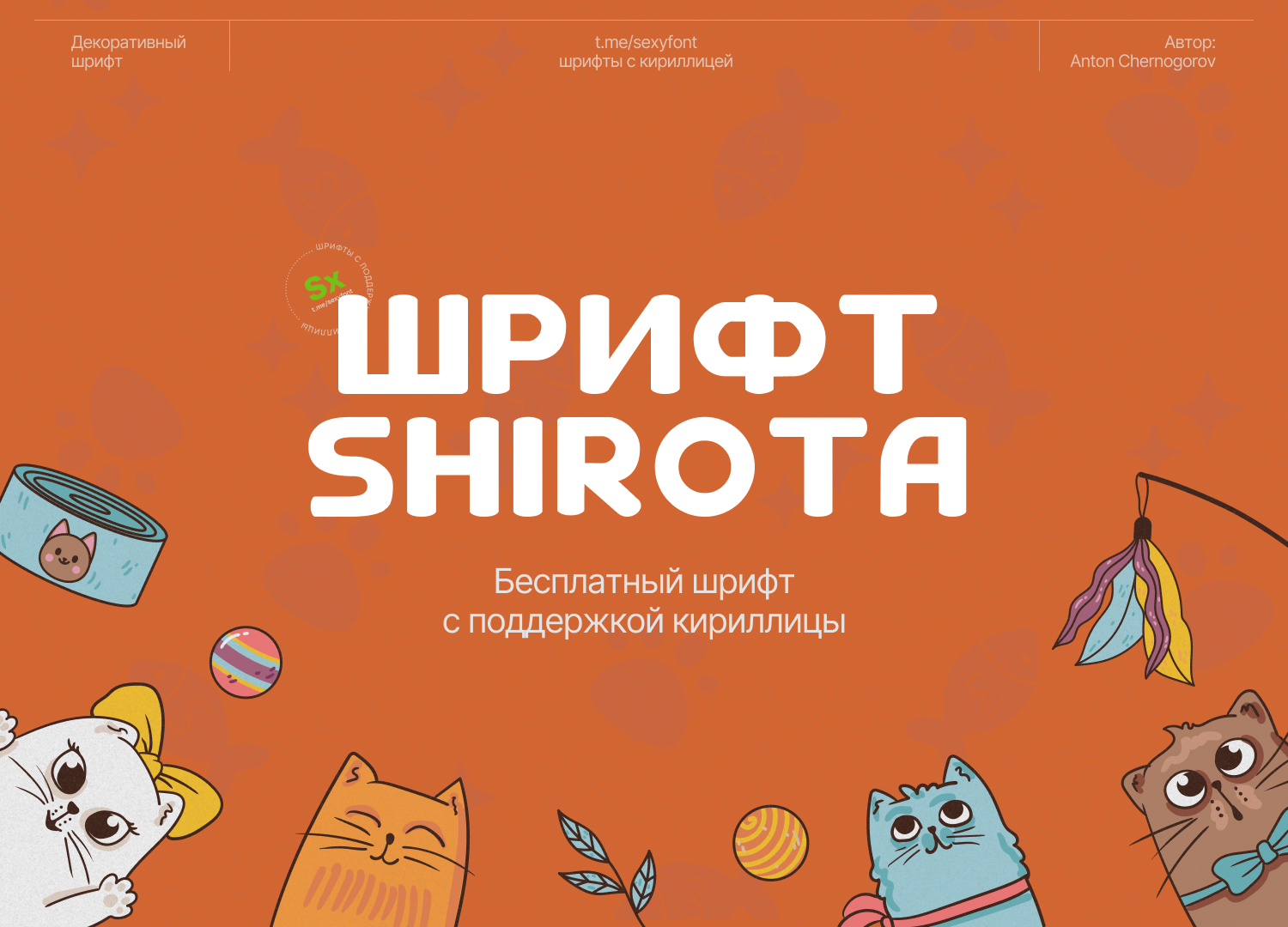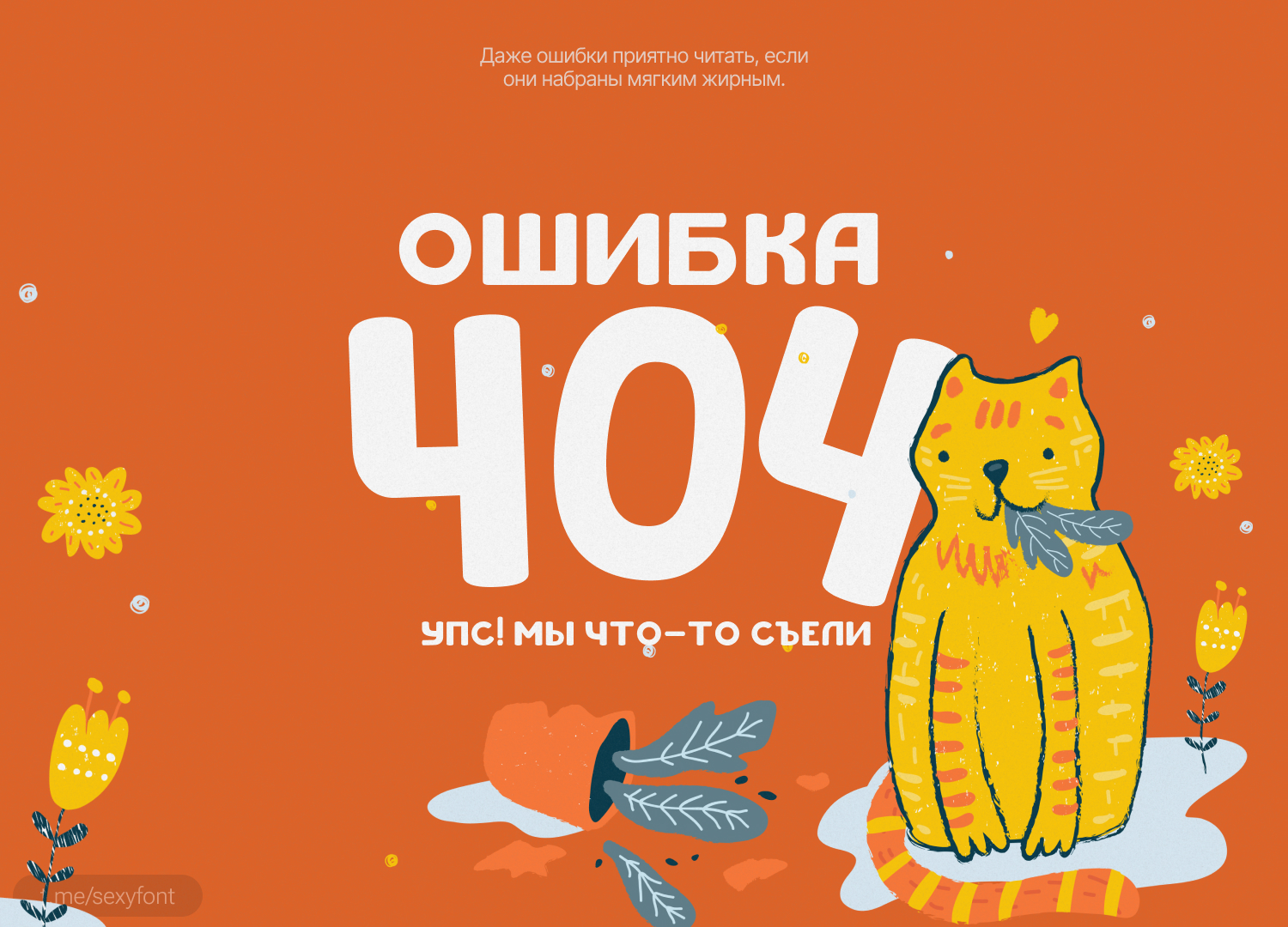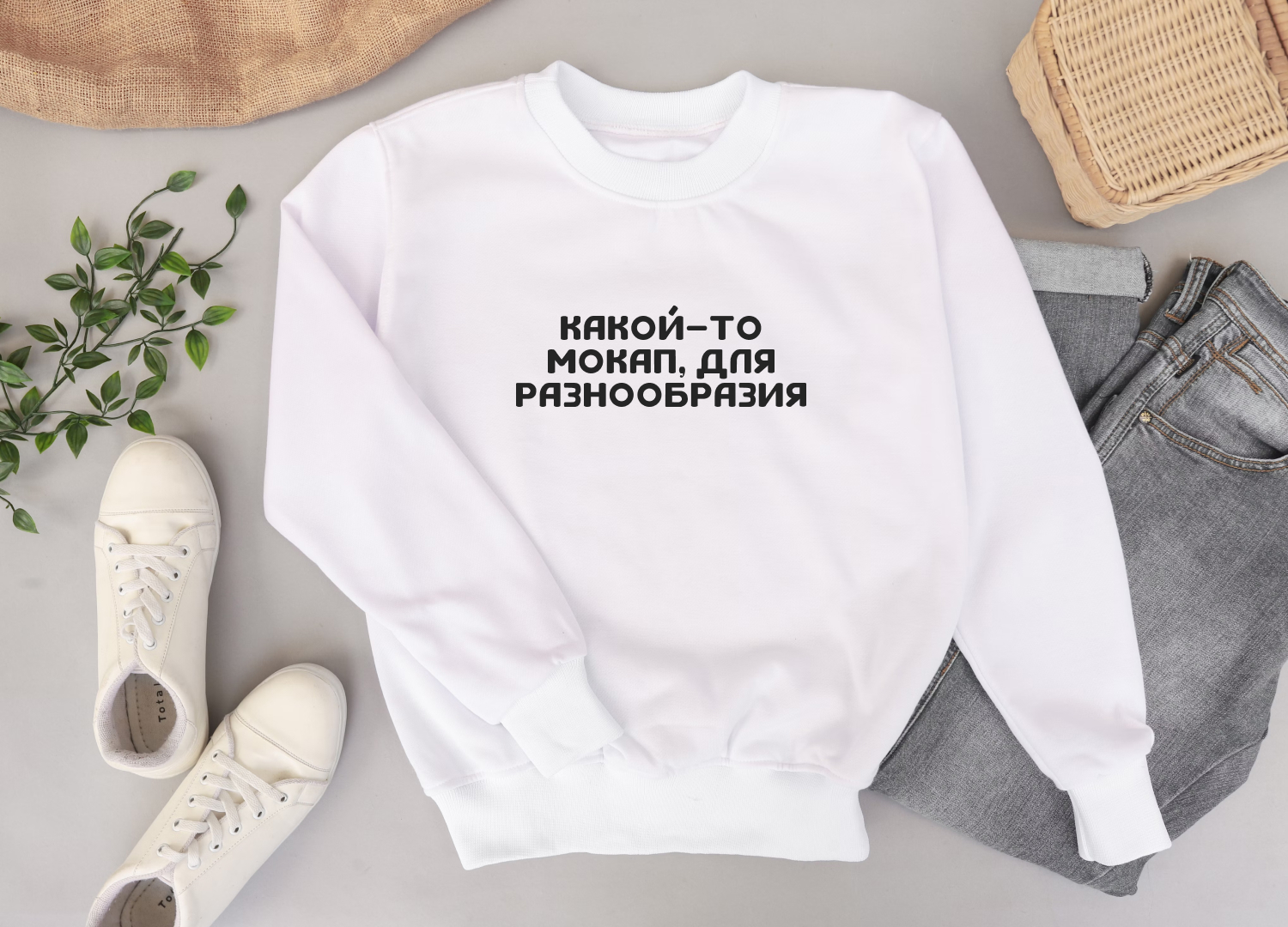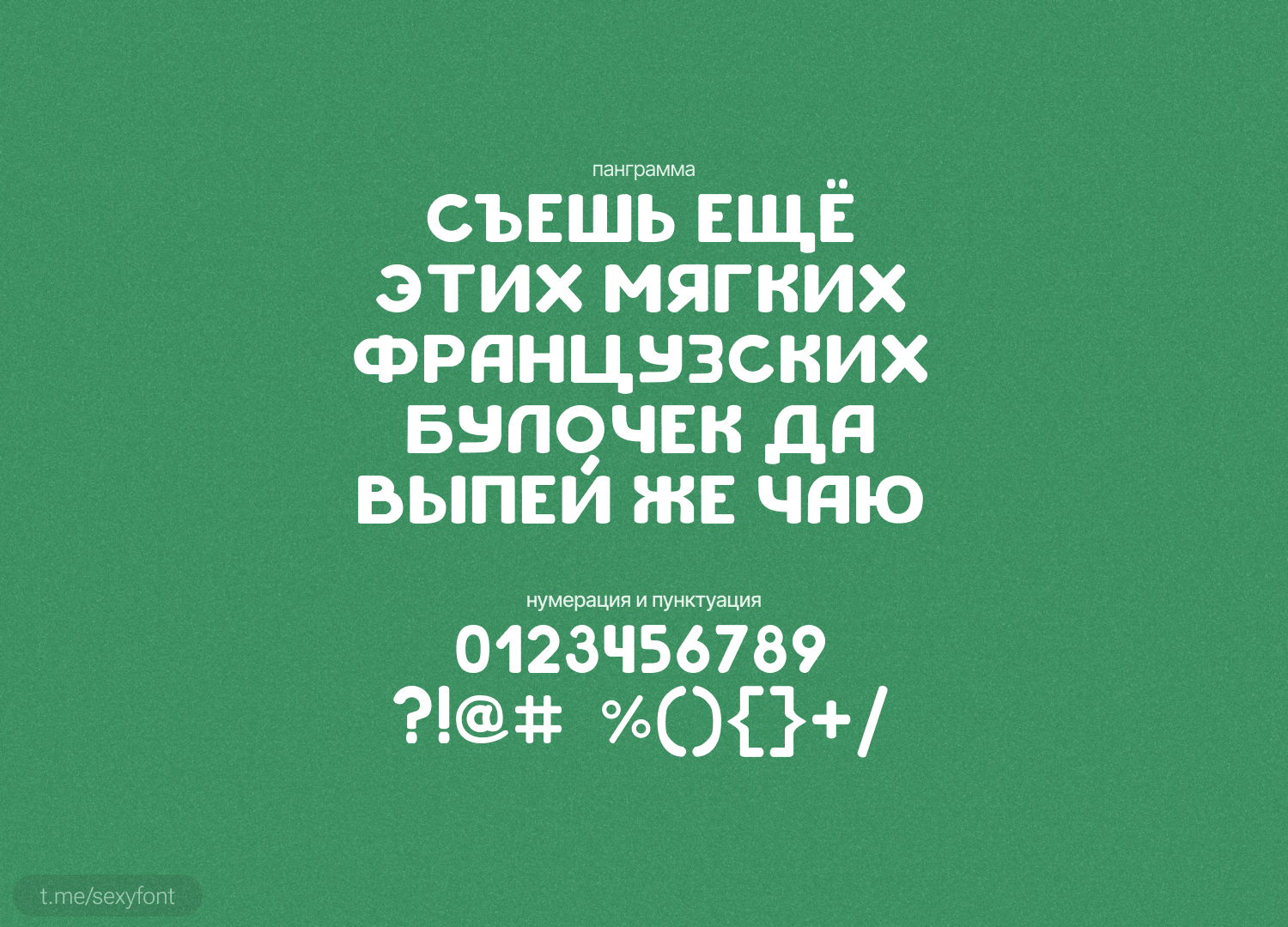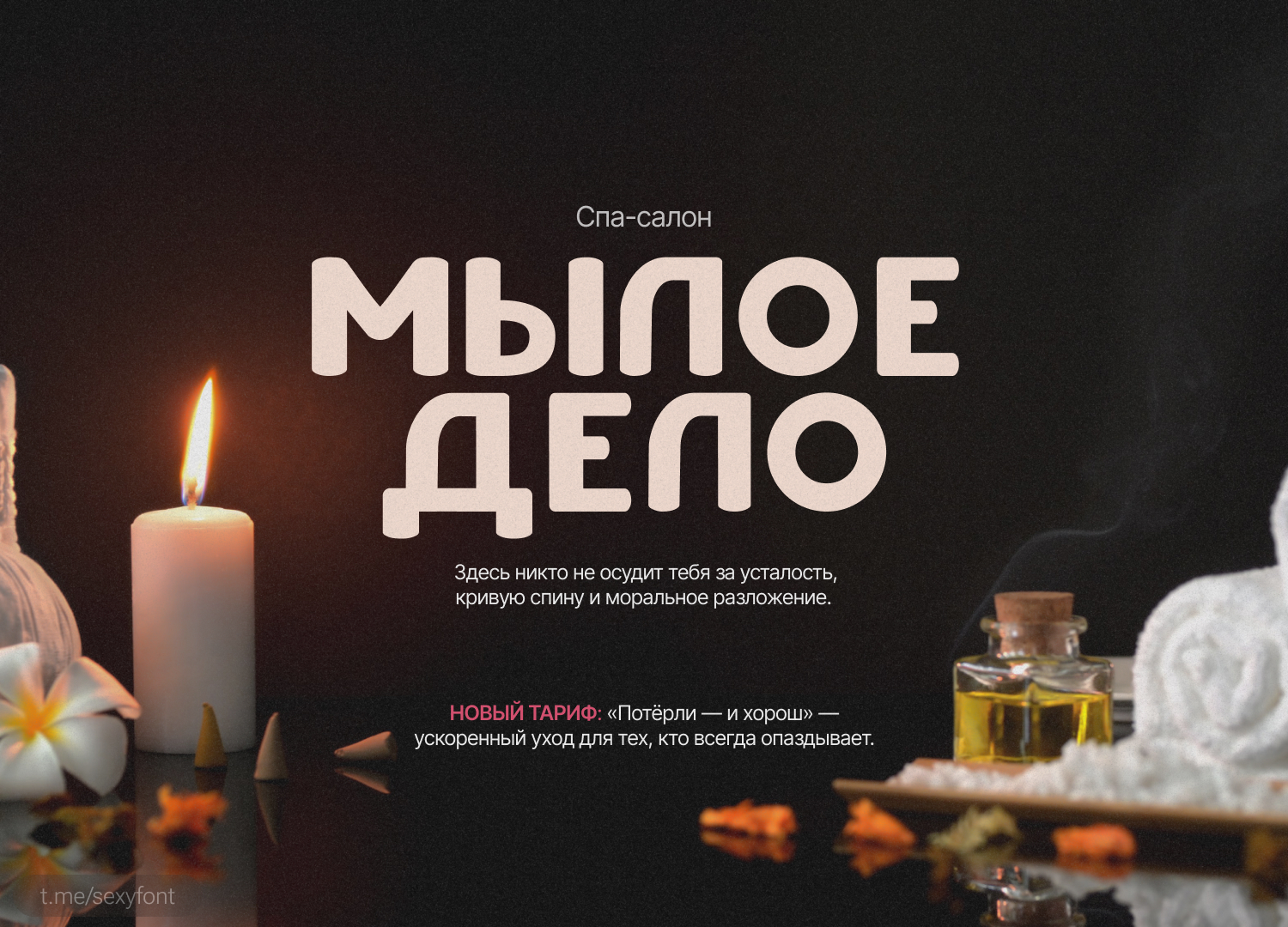
Бесплатный Шрифт Shirota
Заметный пухлый шрифт – широта. Отлично подходит для набора небольшго объема текста. Не теряется на ярком фоне) Естественно поддерживает кириллицу. Но только заглавные буквы.Автор: Anton Chernogorov